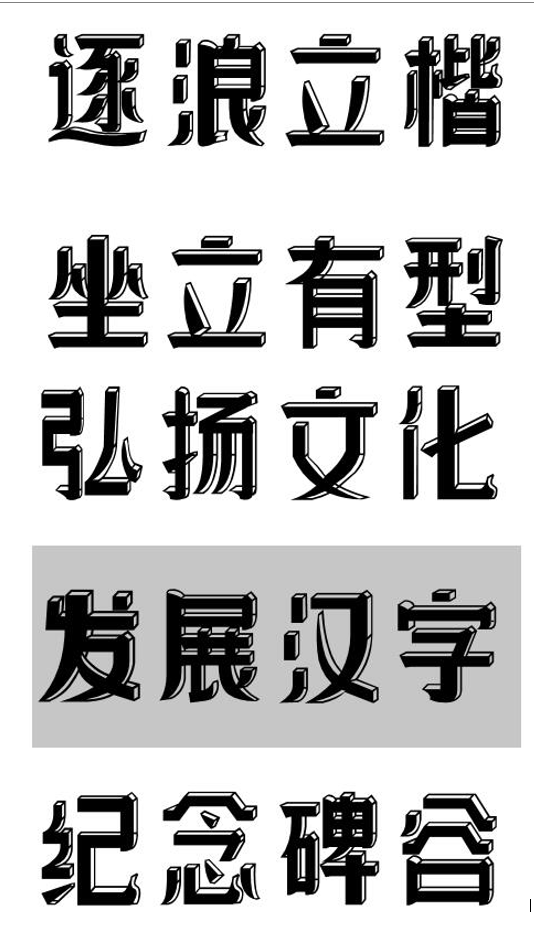
逐浪立楷
缔造不凡,创造卓越的视觉体验!
逐浪立楷,是逐浪字库团队历时一年精心打造的高端字体,已经服务于多个跨国经典品牌,字体引入立体线条造型,具备光面与投影效果。
该字体制作精良,并采用了完全不同的造型体验、立体视觉和线条,是目前中文业界的独创,这也是作为新锐团队和互利网基因的逐浪字库匠人精神的辉煌之作,将千年汉字文化注入时代创新因子,推陈出新,厚积薄发。